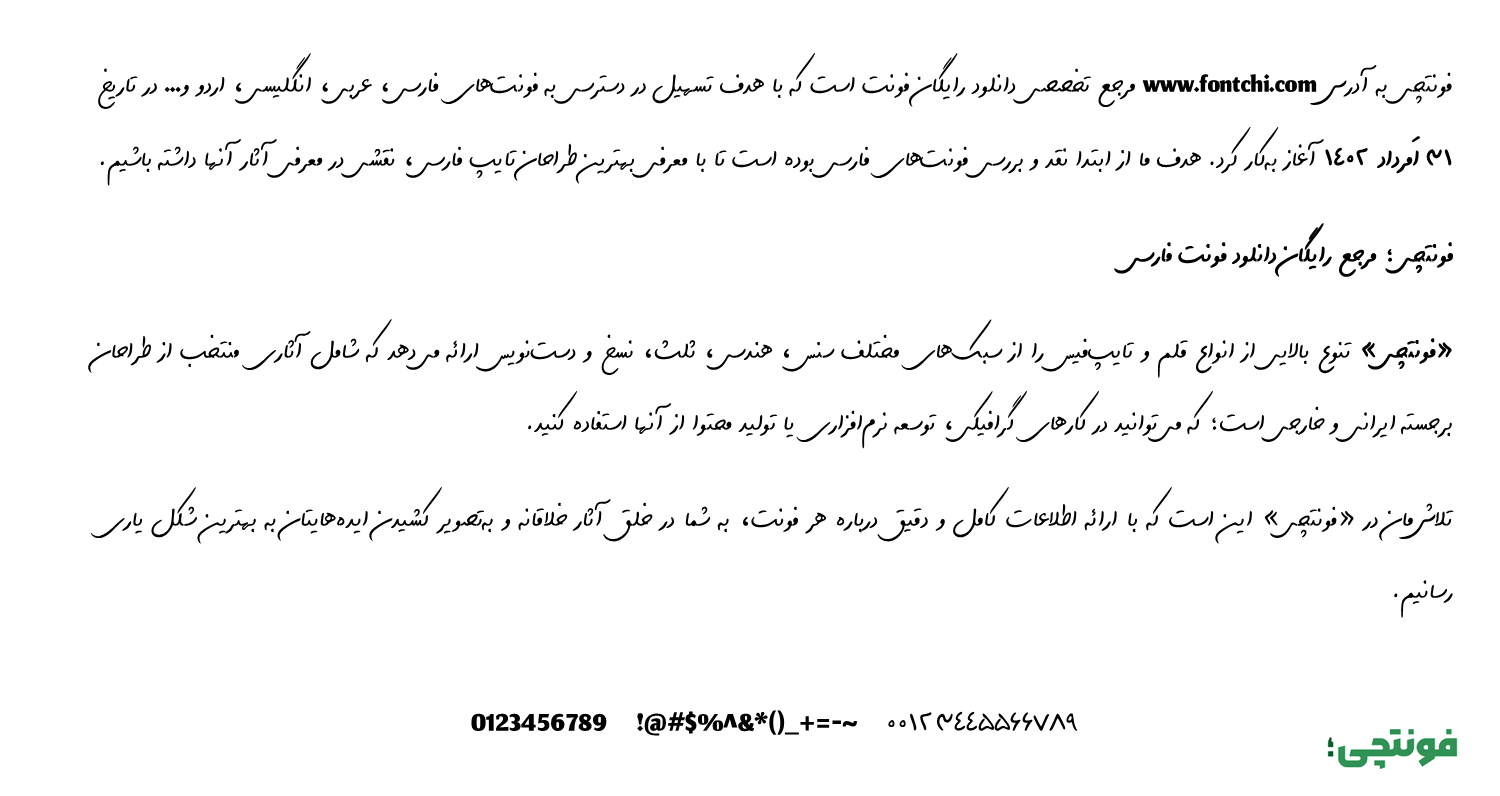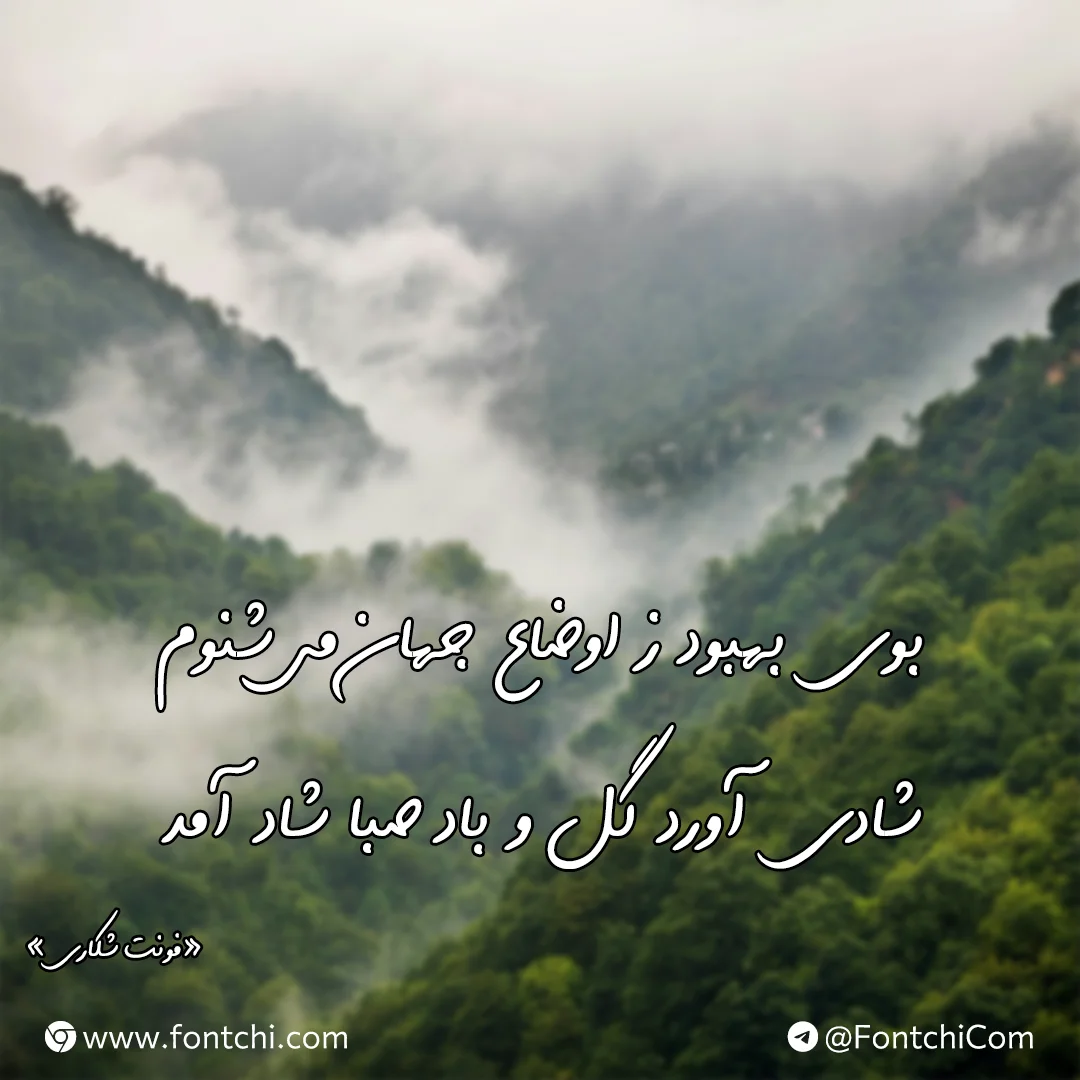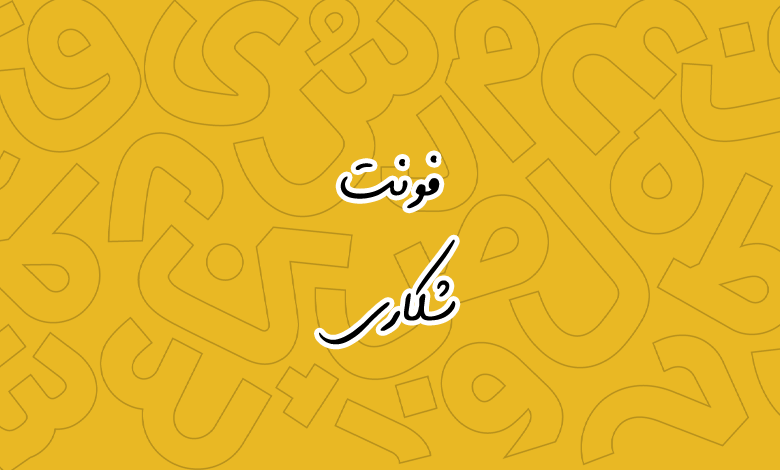
فونت شکاری (A Shekari)
فونت شکاری یا فونت آ شکاری (به انگلیسی: A Shekari) از سری فونتهای فارسی رایگان به سبک دستنویس خودکاری است که میتوانید از آن برای متون کوتاه تا نسبتا بلند استفاده کنید. این فونت فانتزی در سال ۱۳۹۰ توسط امید مرادی طراحی شده و دارای یک وزن معمولی Regular است.
پیش از این فونتهای مختلفی از جمله فونت فر خودکار را در فونتچی معرفی کردهایم. فونت شکاری نیز از دیگر فونتهای به این سبک است که عموما طراحان بر اساس خط شخصی خود آنها را طراحی میکنند. فونتهای خودکاری عموما دارای کاربردهایی مثل عکس نوشته و یادداشت برداری هستند.
فونت فارسی شکاری از زبان عربی نیز پشتیبانی میکند. اما اگر حروف انگلیسی در متن شما باشد، فاقد گلیفهای انگلیسی است و باید از یک فونت جایگزین انگلیسی برای آن استفاده کنید. در نسخه فارسی این فونت نیز یک مشکل جزئی وجود دارد که عدد «۴» با تایپ استاندارد فارسی نبوده و عربی هستند.
در طراحی فونت شکاری برخی حروف دارای ساختاری کشیده هستند که آن را علاوه بر یک فونت خودکاری، به فونتی نمایشی تبدیل کرده که میتوانید در عناوین استفاده کنید. البته اگر نسخههای ضخیمتری از آن وجود داشت میتوانست این ساختار نمایشی در ابعاد بزرگ بهتر خود را نشان دهد.
حروفی همچون «ن، ی، س، ش، ل، ق، ک، گ» طوری تایپ شدهاند که در جملات بلند ساختار خاصی را در کل جمله ایجاد میکنند که به خوانایی فونت در متون بلند کمک خواهند کرد. از اینرو صرفا نمیتوان گفت که این فونت برای متون کوتاه است.
از این فونت میتوانید در اسلایدرهای سایت استفاده کنید. البته استفاده از این فونت برای سایتهای خاص است. برای مثال سایتهایی که یادداشتهایی را در قالب شعر و متون خاصی همچون نقلقولهای ادبی و هنری درج میکنند.